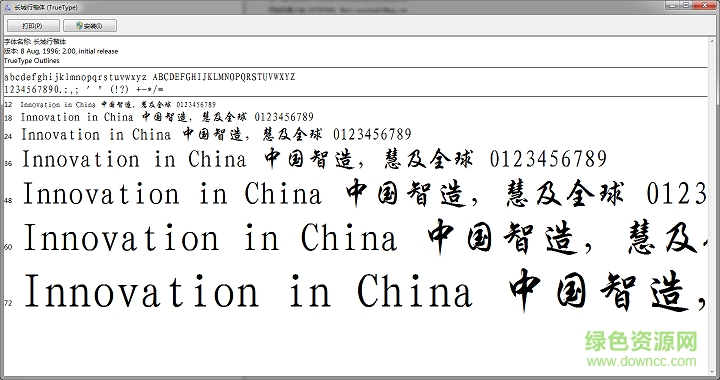
gska00h字體又叫長(zhǎng)城行楷字體,該字體線條靈活,筆畫巧妙,起承轉(zhuǎn)合婉轉(zhuǎn)有度,形態(tài)十分瀟灑,藝術(shù)效果極佳,喜歡的小伙伴趕緊來綠色資源網(wǎng)下載下載收藏吧!
非常漂亮的書法字體,長(zhǎng)城行楷字體不僅能夠幫助用戶提高對(duì)書法的認(rèn)識(shí),還能夠幫助用戶練習(xí)長(zhǎng)城行楷字體,提升用戶的書法水平,長(zhǎng)城行楷字體極具書法范,應(yīng)用到國(guó)內(nèi)的很多領(lǐng)域,受到很多書法愛好者的喜愛
本款字體偏向于行書字體,字體端正、大氣,筆畫非常的細(xì)膩,連筆流暢又不失整潔,可用于廣告印刷和包裝設(shè)計(jì)等行業(yè)!